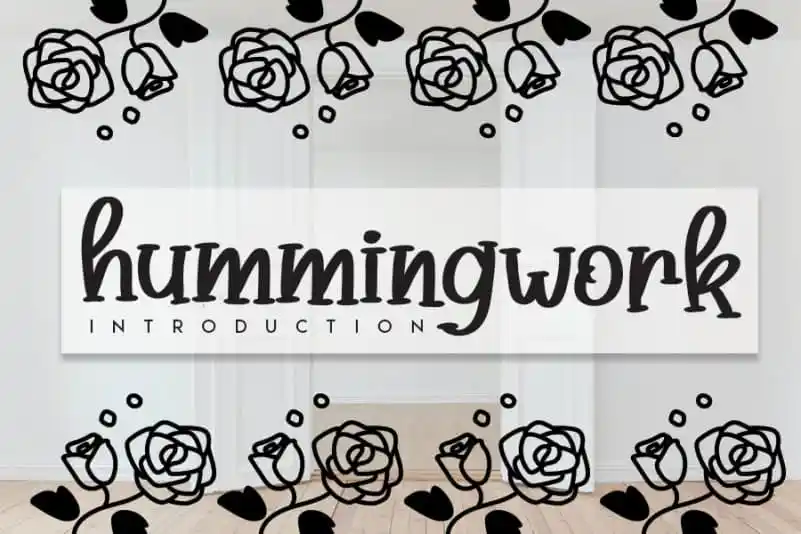
Hummingwork Script Font – Download Grátis
A “Hummingwork Script Font” é uma elegante fatura de escrita a mão que se destaca tanto para projetos formais quanto informais. Suave e limpa, ela oferece um toque único e inovador às criações digitais, tornando-as mais atrativas e memoráveis sem perder sua simplicidade. Seja você um designer profissional ou iniciante, essa fonte irá enriquecer suas ideias criativas, destacando-se entre as demais no seu próximo projeto. Escolha a “Hummingwork Script Font” para adicionar um toque pessoal e único às letras digitais que você cria.